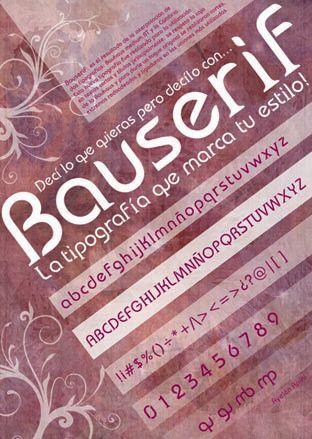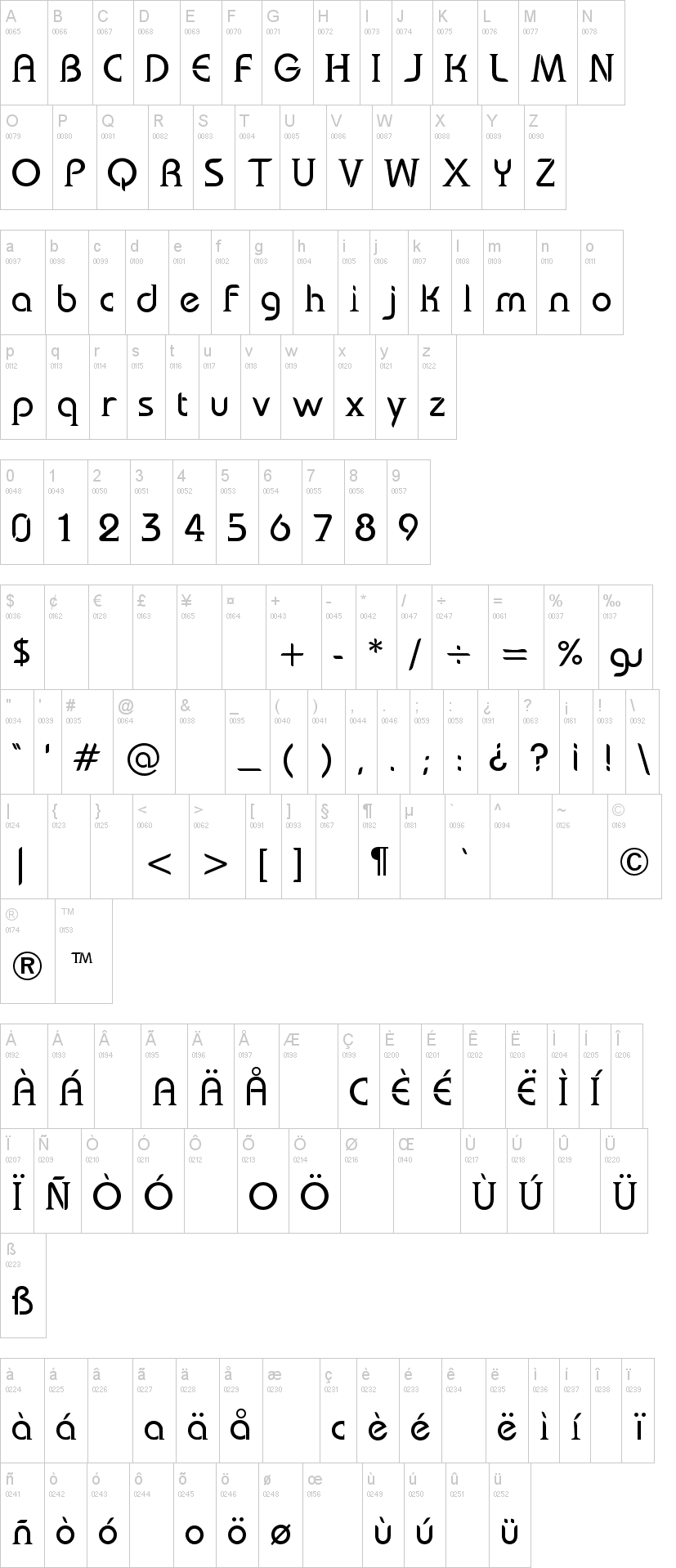
Шрифт Bauserif
BauseriF: es el resultado de la interpolación de dos tipografías: Bauhaus medium BT y la Cambria. Esta nueva tipografía fue realizada para la utilización en textos cortos y títulos principalmente; se respeto la caja de la Bauhaus y para darle un toque original se realizaron cortes, extremos redondeados y ligaduras en las uniones más utilizadas.